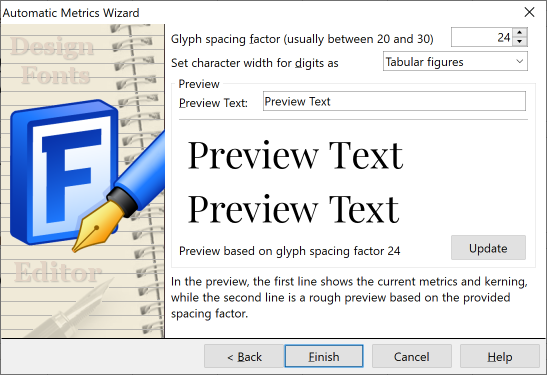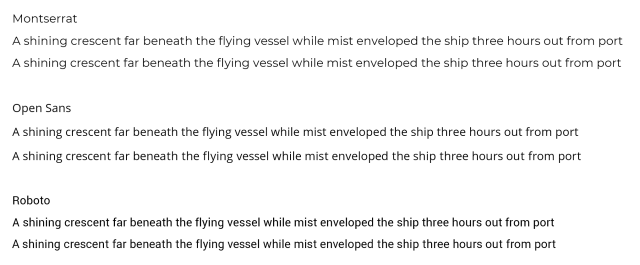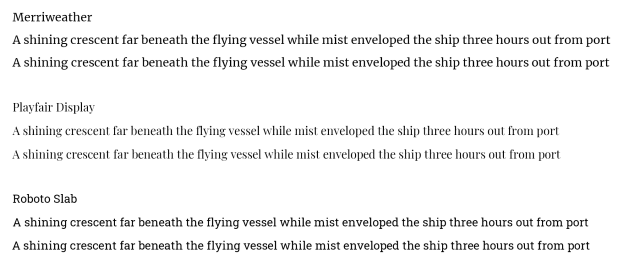
No.15 Glyph Spacing
字形间距与 光学度量
字体设计最重要的任务之一,就是为字形之间提供平衡的间距。这件事繁琐且容易令人厌烦——但配合光学度量则不然!
在设计字体时,您可以添加字符和字形,而不必过多担心每个字形的度量,但在考虑向字体添加字距之前,必须确保字形之间的间距是最佳的。
字体编辑器通常有几种方法来调整每个字形的侧边距,但 FontCreator 专业版允许您以光学精度为拉丁字符生成这些度量。只需打开自动度量向导(通过工具 → 自动度量菜单可用),并使用光学度量选项在每个字符之前和之后生成最佳光学空间。您可能需要尝试不同的字形间距因子,这允许您提供全局距离因子。较大的因子将导致字形之间有更多间距。
自动度量向导
我们选取了几种流行的字体,以便您可以看到此功能的强大之处。下面您可以看到原始字体(第一行)以及运行光学度量后的字体(第二行)。两者的字体大小均为 14。未应用字距,因为这会覆盖间距。
无衬线字体:
无衬线字体比较
衬线字体:
衬线字体比较
对于衬线字体,您可以看到光学度量很难为带有碗状的字形计算良好的值,例如组合 "be"、"pe" 和 "po"。我们可能需要调查这一点以进一步改进算法。
光学度量每个字体花费不到一分钟。如果您意识到字形间距被认为与字形轮廓的设计一样重要,这还不错。字体设计师可以不使用光学度量,但他们通常花费数小时试图找到良好的平衡。我们不明白为什么其他字体编辑器还没有为此提供自动化功能,但目前,您可以从中受益,而其他字体设计师则在手动间距方面挣扎。
字形之间的完美间距使字体脱颖而出,并避免了不必要的字距对。